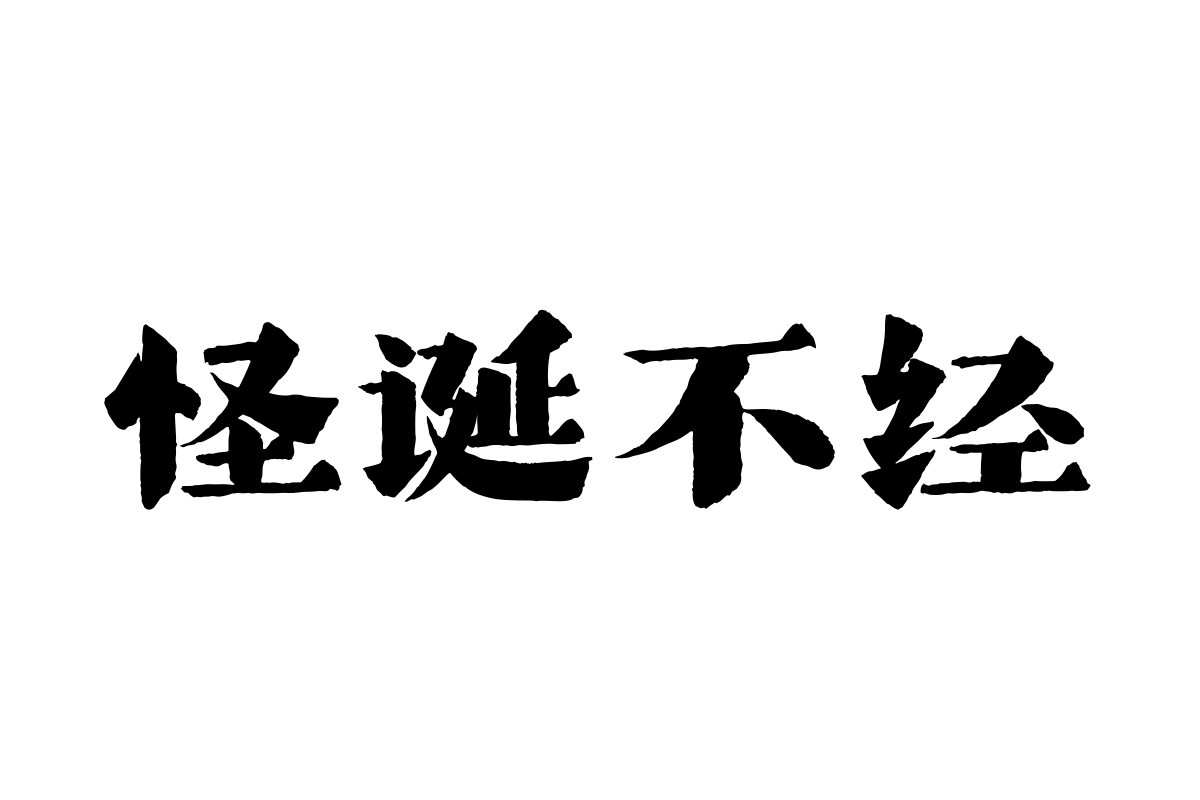
汉仪大椿手绘宋字体是一款具有中国传统书法风格的字体,由汉仪字库出品。这款字体以宋代书法为蓝本,结合现代设计元素,创造出一种既具有传统韵味又不失现代感的字体。
该字体的特点如下:
1. 字形规整,笔画流畅,具有较强的视觉冲击力。
2. 结构严谨,比例协调,适合用于各种文字设计,如标题、正文、广告等。
3. 风格独特,融合了宋代书法的精髓和现代设计的理念,给人以古朴典雅的感觉。
4. 适用于多种场景,如书籍、杂志、报纸、网站等,具有较高的适用性。
总之,汉仪大椿手绘宋字体是一款具有浓郁中国传统文化特色的现代字体,适合用于需要展现传统文化气息的文字设计。